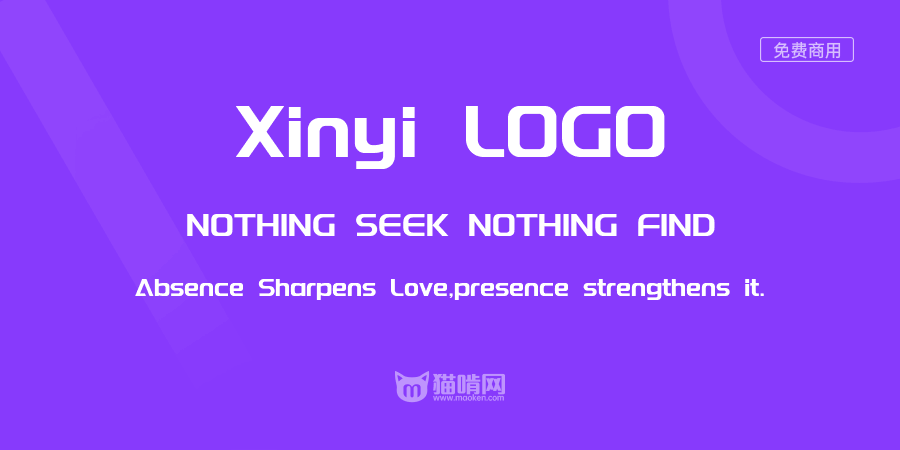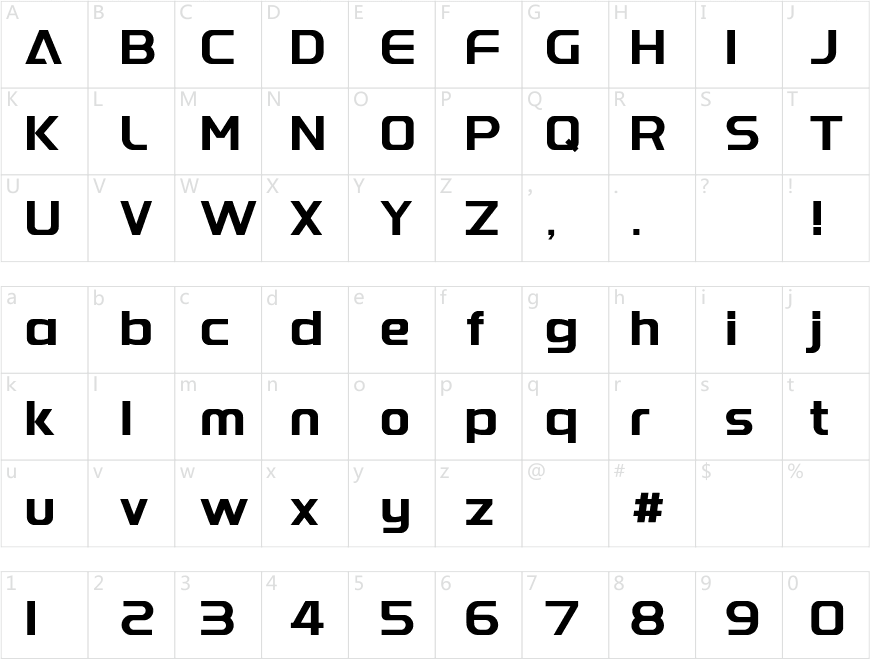
Xinyi LOGO
这是一套全英文字库,适用于标题、LOGO设计等场合使用,所以只做了52个英文10个数字和几个标点。
这套字巧妙之处在于,如果你的公司需要设计LOGO,但你不会做LOGO设计,你可以把字打出来,调个间距,调个颜色,国际化立马飙升!
比如你看看下面这些案例,你就会明白,无论是互联网公司,还是服装品牌,还是玩具公司,还是食品公司,还是大型企业等等,都是很适合的!
对于后面这款字的介绍少了些,但是我的朋友们反应都不错。好了,至此展示完毕。《字体圈欣意冠黑体》《字体圈欣意LOGO体》是永久免费商用!